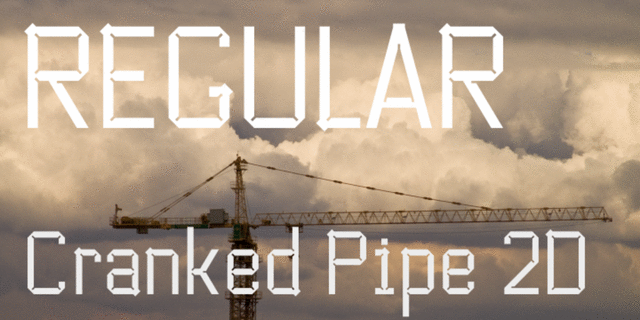
Шрифт Cranked Pipe имеет индустриальные мотивы и простой модульный геометрический рисунок. Он предназначен для работы в крупном размере, например, в городской суперграфике. Этот шрифт содержит символы множества языков на все случаи жизни, много лигатур, альтернативы, росчерки и другие опентайп-фичи. Шрифт разработал Лукьян Турецкий в 2011 году.